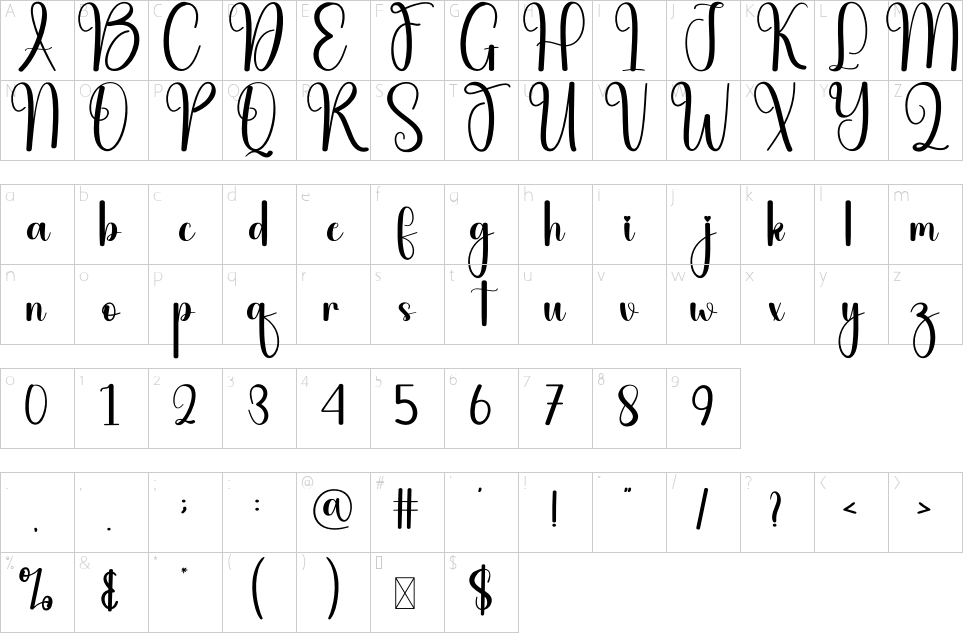
Descubra a beleza da Amastay Font, uma elegante e versátil opção para designers gráficos do Brasil. Introduzida pelo talentoso designer william jhordy, a Amastay é uma fonte que busca equilibrar modernidade com clássico, oferecendo uma paleta de estilos que vai do clean e minimal ao elegante e detalhado. Sujeitada ao uso para múltiplos projetos, a Amastay é perfeita para criações no Windows e Mac. Com uma facilidade de uso e um design que promete manter sua identidade gráfica ao longo de seu trabalho, a Amastay é uma fonte que vale cada download. Com seu design cuidadosamente pensado, você pode garantir que a sua obra seja notável, tanto no seu dia a dia quanto em suas obras maiores. Se você está à procura de uma fonte de qualidade sem precisar gastar um centavo, a Amastay é uma opção ótima.